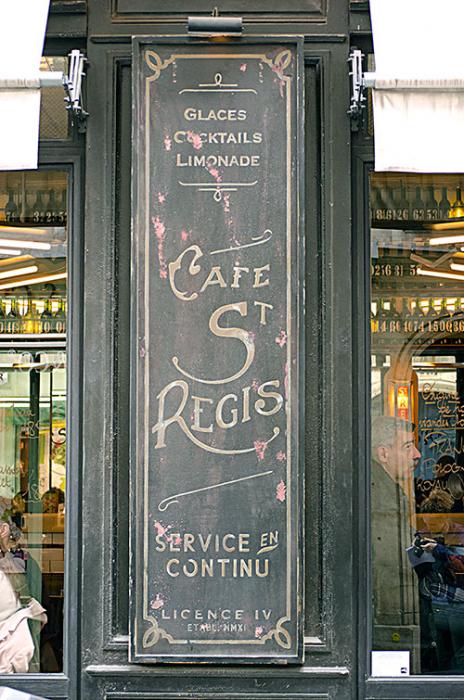
Historische Schrift gesucht
dieses Schild habe ich in Paris entdeckt. Ich bin auf der Suche nach einem Schriftmuster: Vorbild ist die Schrift für den Text CAFE ST REGIS. Wisst ihr aus welcher Epoche die Schrift stammen könnte?
Vezeih mir bitte wenn ich nichts wirklich konstruktives beizutragen habe, aber ich seh darin (eines von vielen) Beispielen, die belegen, dass die oft aus nostalgischen gruenden hochgelobten Schriftenmaler aus vorfolienplotzeiten auch oft genug typografisch zweifelhaftes produziert haben.
Die Ästhetik und die Handwerklichkeit wird hochgelobt, nicht die typografische Qualität. Lies mal Tschicholds „Meisterbuch der Schrift“.
Wie gesagt, mich interessiert nur die Einordnung der Schrift :)
Vorbild wirst du kaum finden, Epoche: Rund um 1900. Hier haben sich eben ein Heer an Schildermalern am Zeitgeshmack mehr oder weniger Erfolgreich bemüht, etwas brauchbares an die Wand oder auf ein Schild zu malen. Dabei hat man sich eben auch an allem orientiert, was es damals so gab
Ich dachte, dass eine größere Anzahl an Schildermachern sich eher an Vorlagen orientiert hat. Viele von ihnen waren ja Dekorationsmaler und hatten keinen besonderen Bezug zur Typografie, daher überrascht es mich, dass es auch experimentell arbeitende Schildermacher gab.
Bist du dir sicher, dass es dafür keine Vorlagen gab?
Sicherlich gab es so einige Musterbücher für Schildermaler, aber auch diese bestanden kaum aus Satzschriften, sondern waren eben speziell für das Lettering von Grafikern und Kalligrafen gezeichnet. Wenn der Schildermaler in diesem Falle eines verwendete, dann bestimmt auch eines ausd Frankreich, und die kenne ich leider nicht. Zudem war diew Ausbildung der Schildermaler durchaus mehr an freierer Gestaltung von Schriften ausgerichtet.
Hier ein Schildermaler-Schriftmusterbuch aus dem Ende des 19. Jahrhunderts:
Die Arbeit oben hat aber, wie andere ja auch schon sagten, sicher keine direkte Vorlage. Insbesondere der mittlere Teil ist sicher frei für dieses Schild und die speziellen Buchstaben entworfen worden.
Du musst dich gedanklich nur mal in die Zeit zurück versetzen. Damals waren wirklich ALLE Laden- und Gasthaus-Schilder vom Schildermalern handgeschrieben, und die Zahl unterschliedlcher Unternehmen war ebenfalls weit größer als heute, da es kaum Ketten gab. Ebenso war es mit Werbung auf Verkehsmitteln. Wer aslso damals als Schildermaler dein Brot verdienen wollte, musste eigentlich nur mit offenen Augen durch die Stadt gehen, und hatte Vorlagen zu Hauf